Akzidenz Grotesk Next
2007(Berthold)
「アクチデンツ・グロテスク」は、ヘルマン・ベルトルト(1831-1904)のベルトルド活字鋳造所が1896 年に発表したサンセリフ体で、後に誕生した「ヘルヴェチカ」のもとになったとも言われています。2007年には「アクチデンツ・グロテスク・ネクスト」が発売されました。
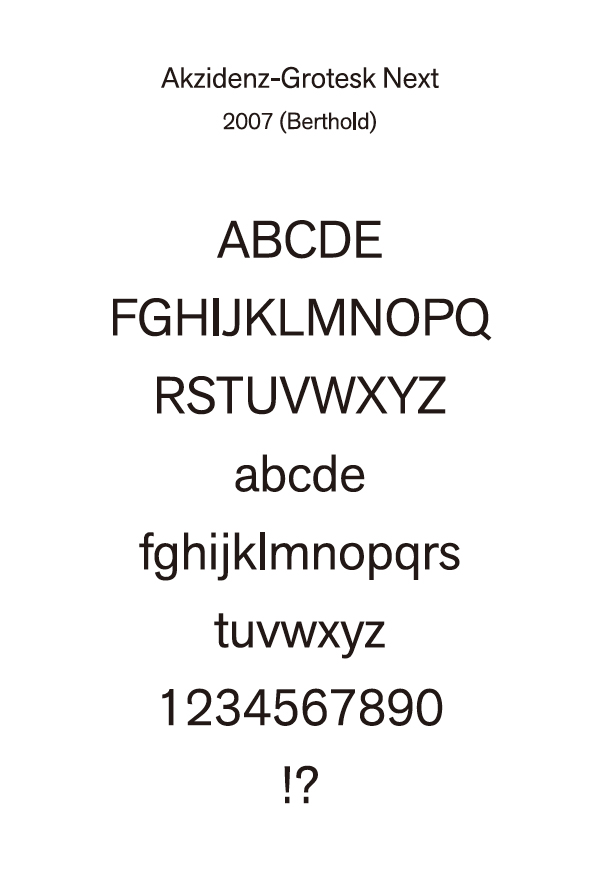
Franklin Gothic
David Berlow, Morris Fuller Benton ,Victor Caruso,1904-1906(Linotype)
「フランクリン・ゴシック」は、1903年から1912年にわたって、ATFのためにモリス・フラー・ベントン(1872-1848)によって設計されました。初期のサンセリフ体は、アメリカでは「ゴシック」という誤称で知られました。ベントンは多作のデザイナーであり、ニュース・ゴシック、オルタネート・ゴシック、ライトライン・ゴシックなど、いくつかのサンセリフ体を設計しています。